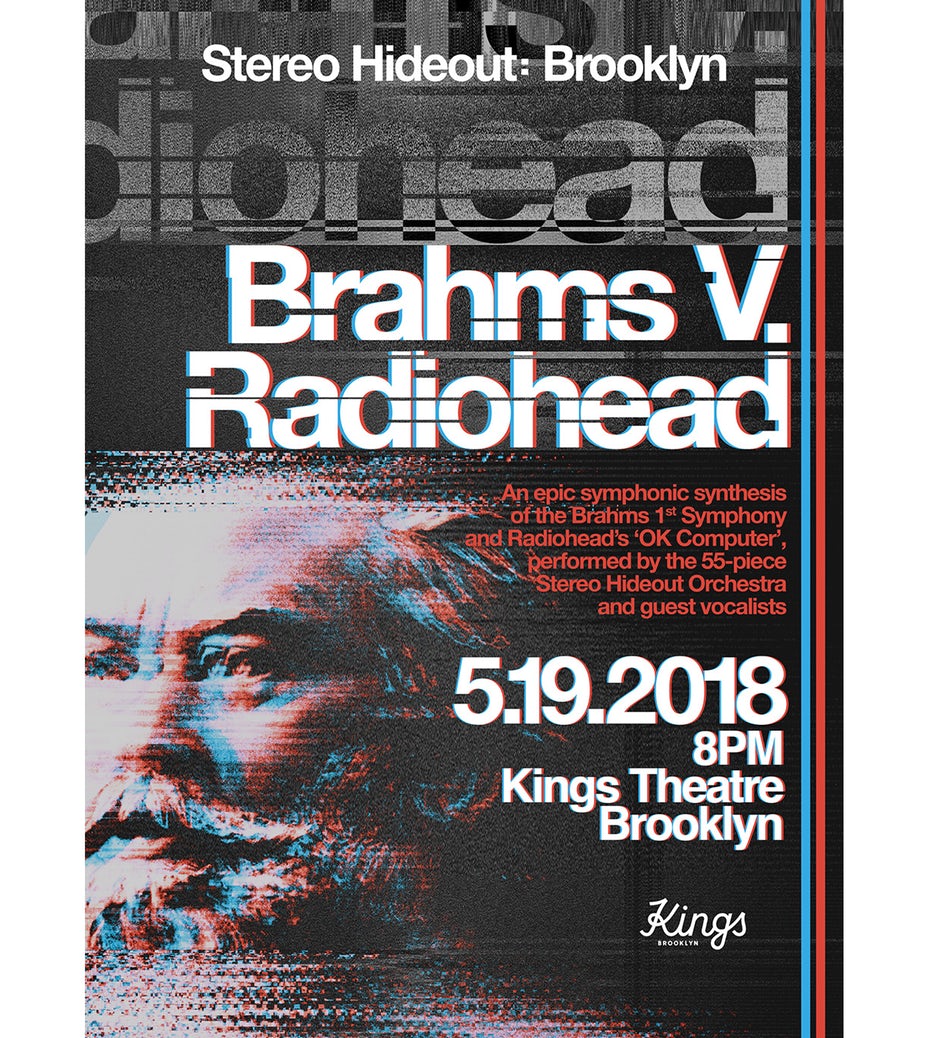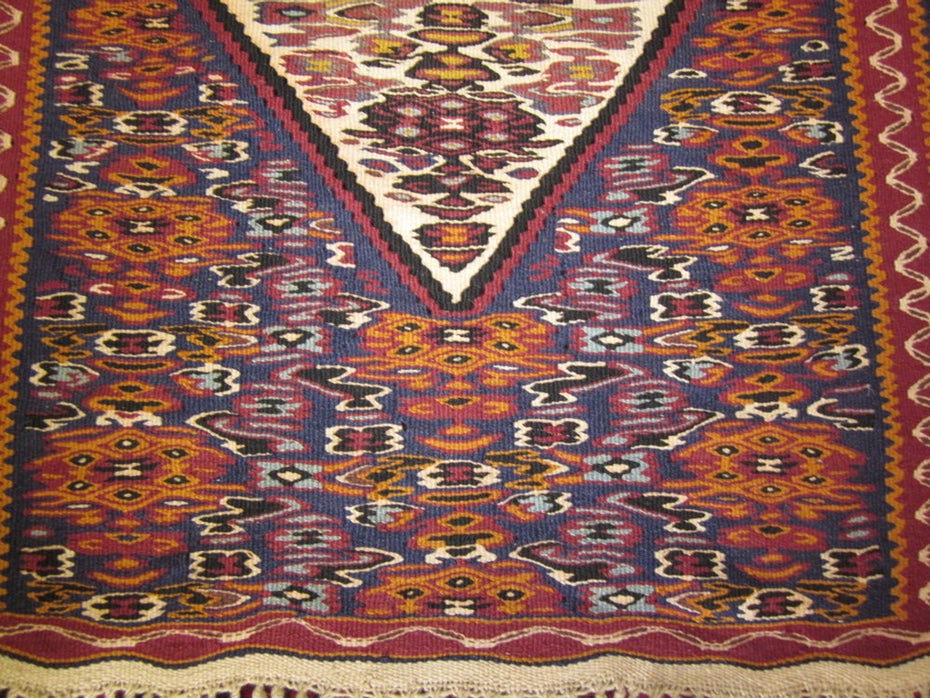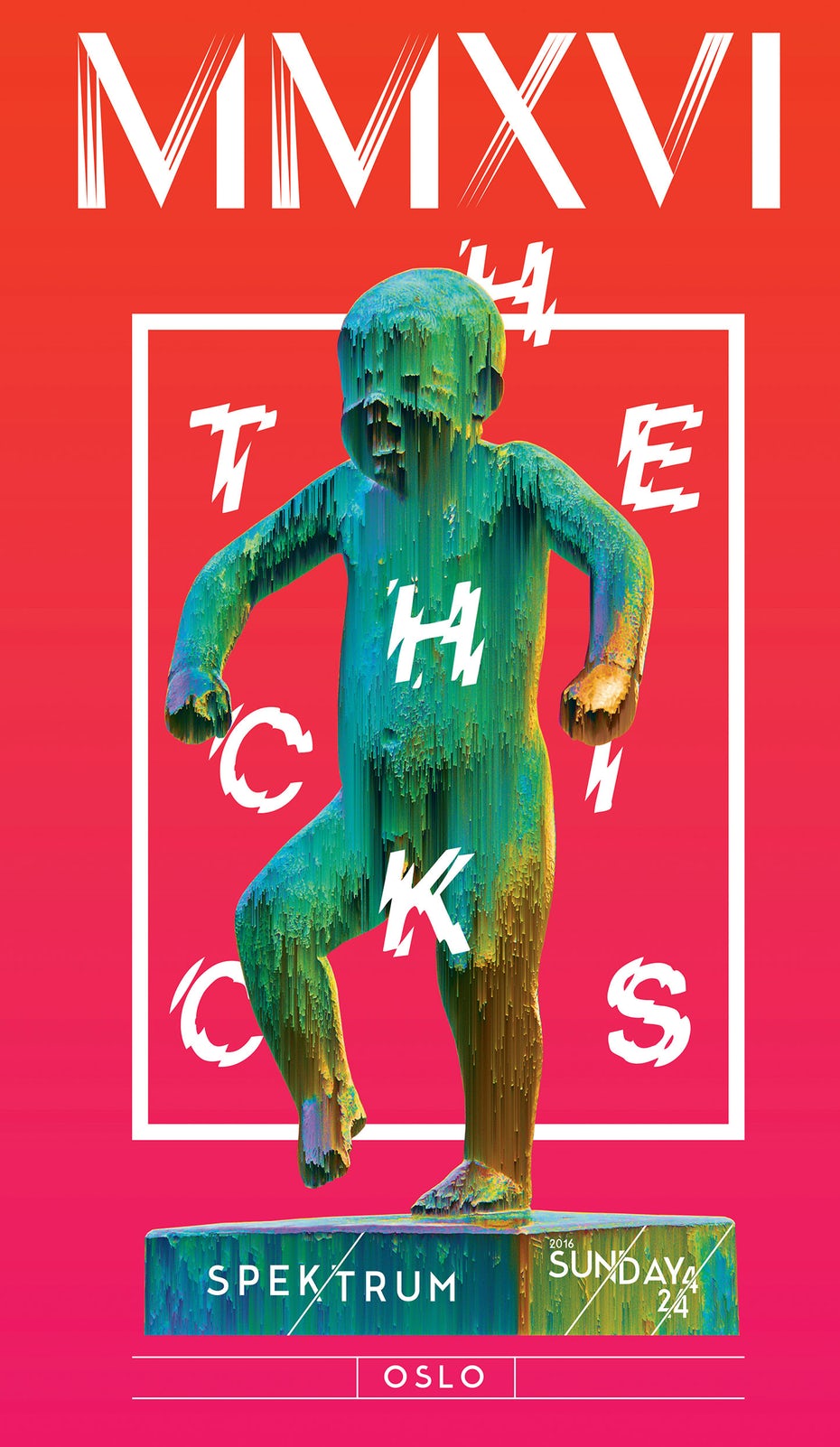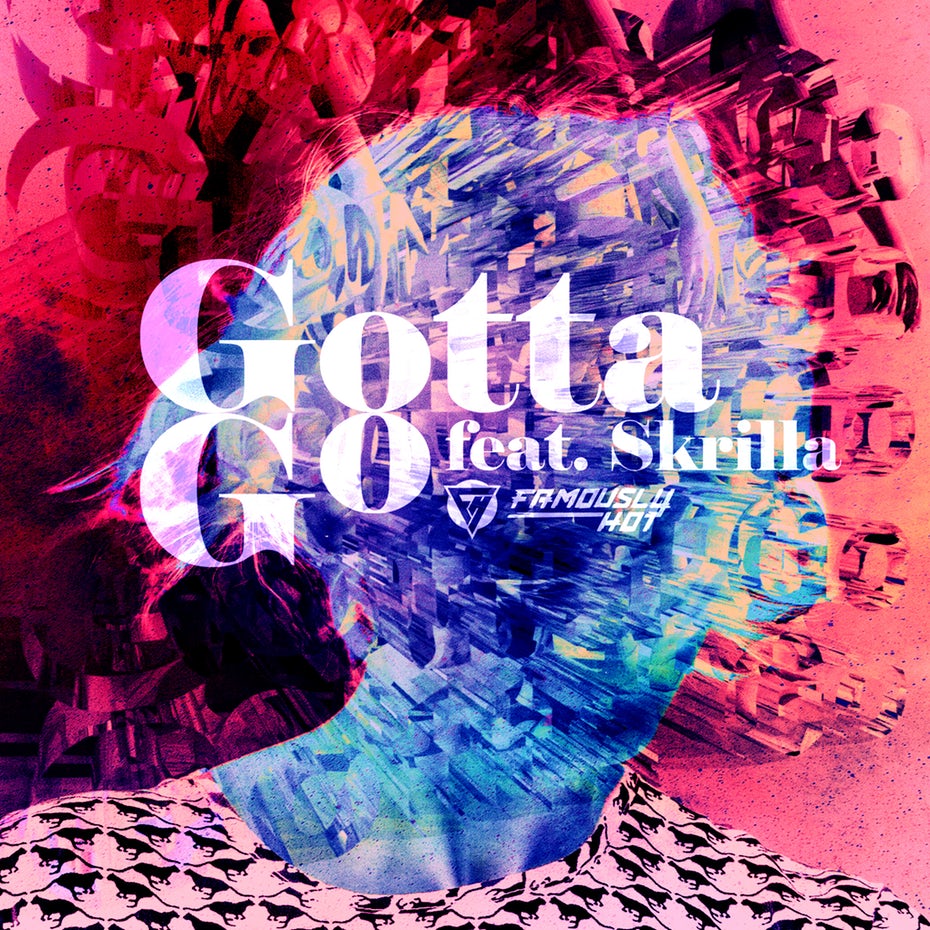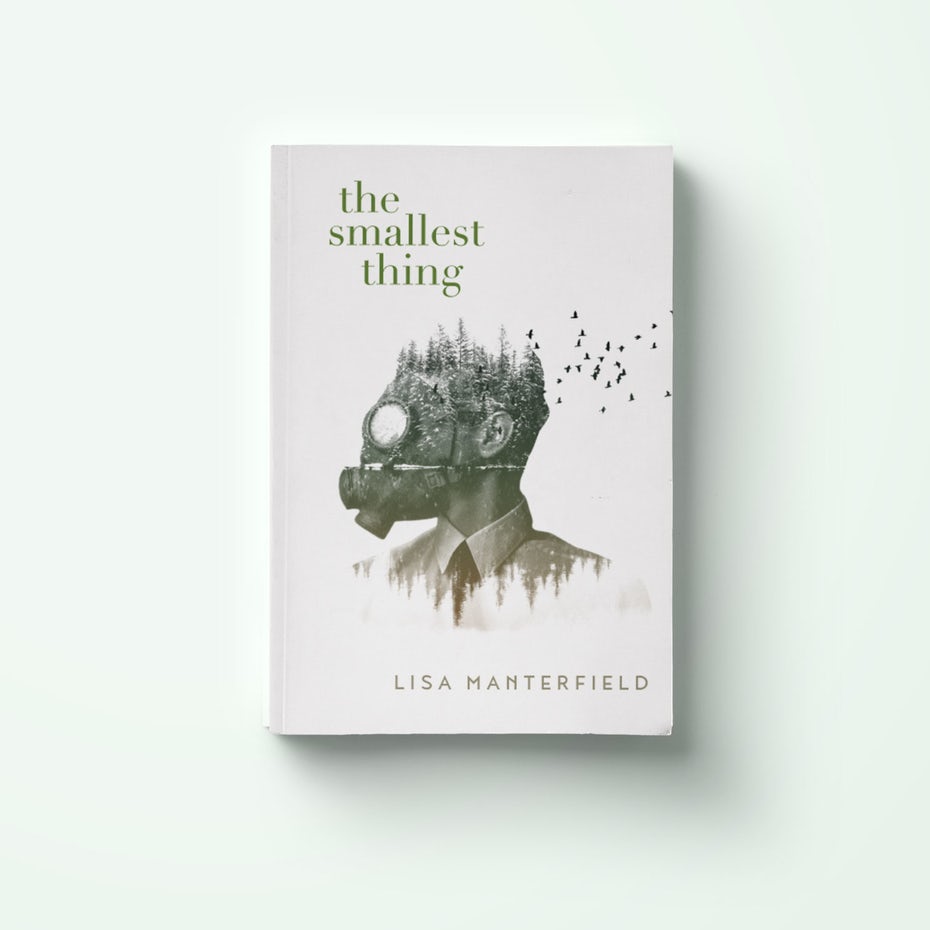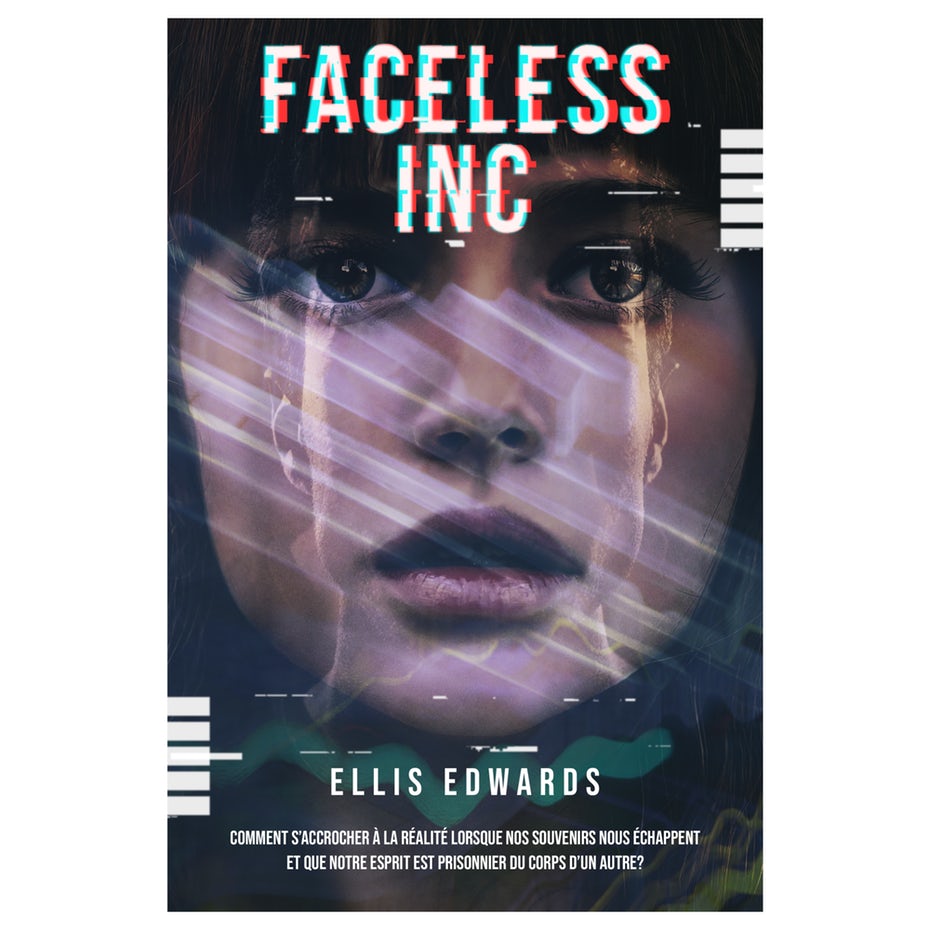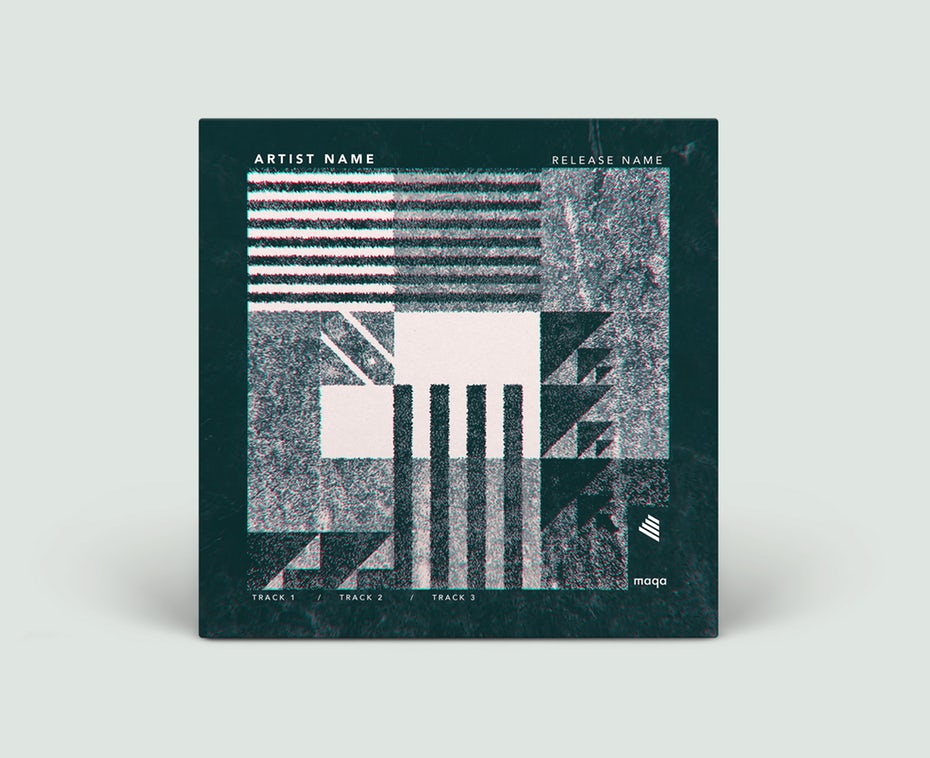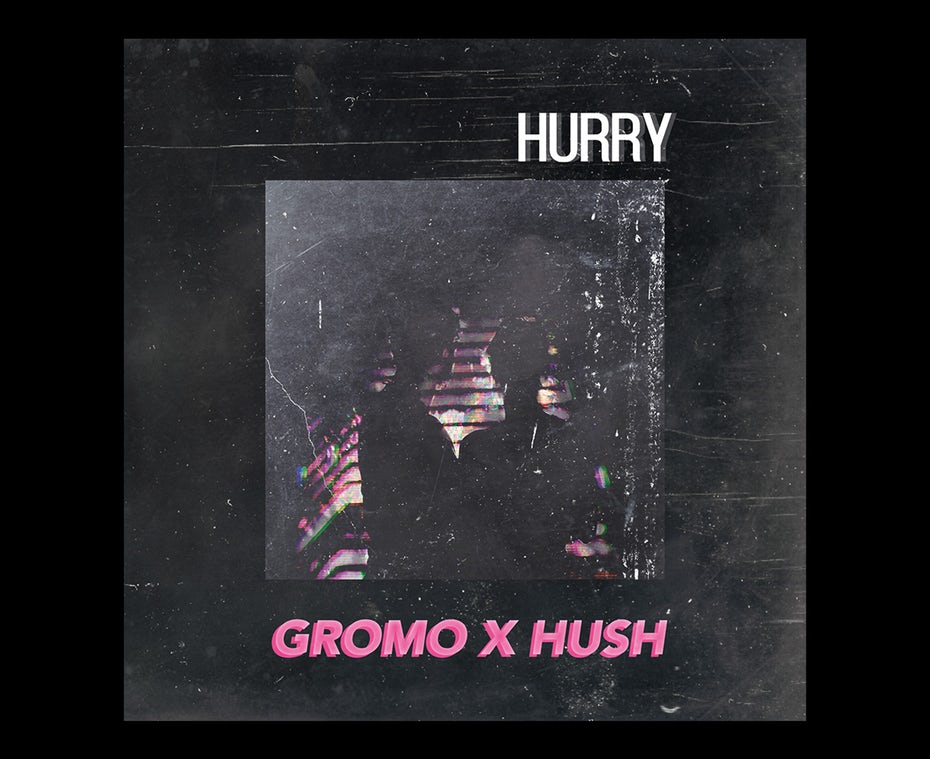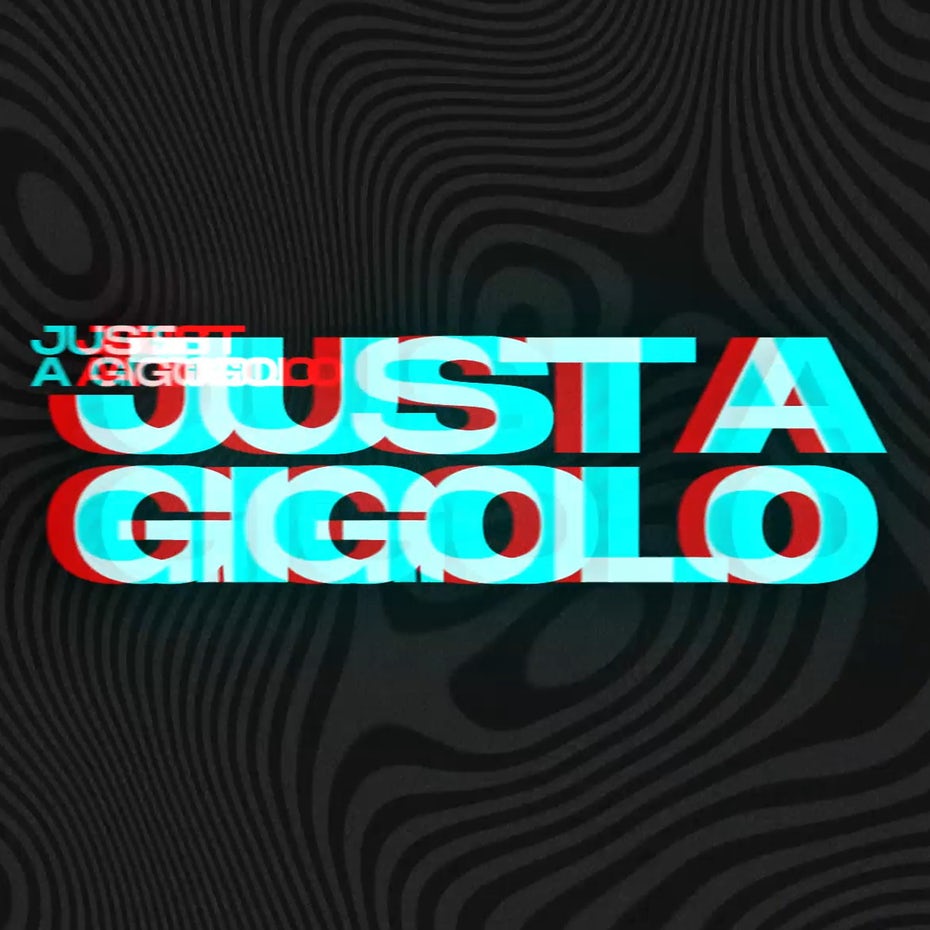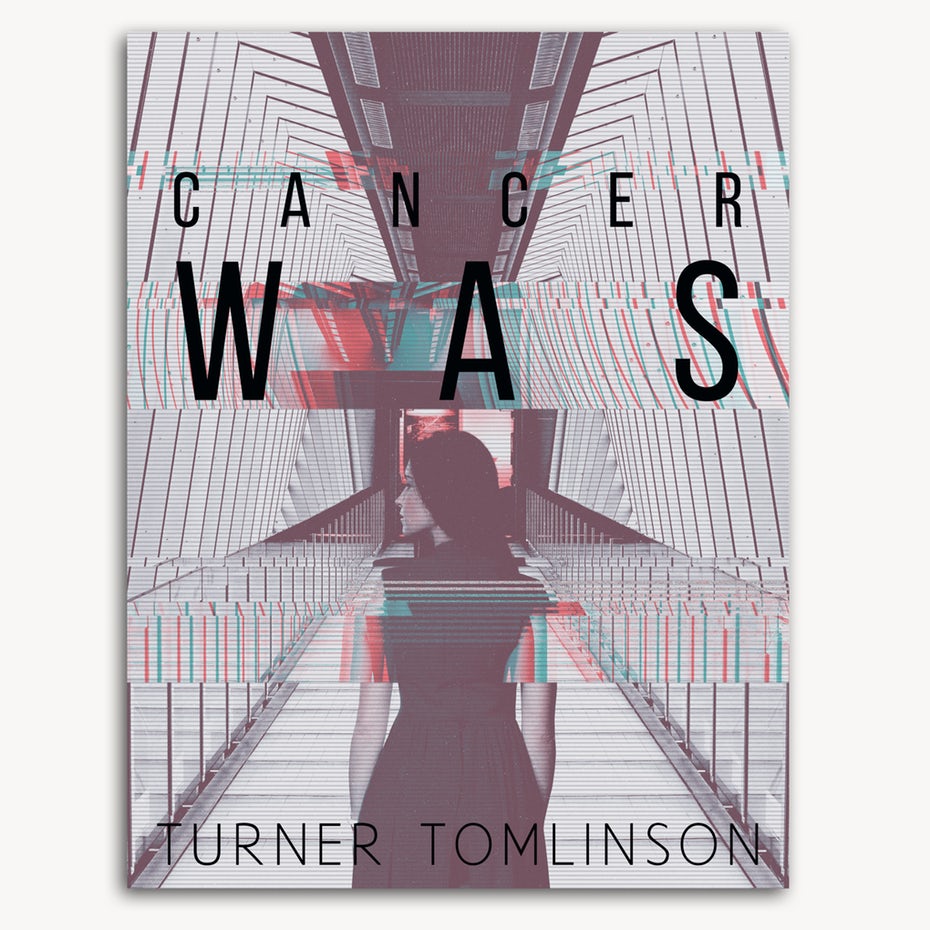
故障艺术设计教程:历史的内观与现代潮流的最佳运用
魔术贴,冰棒和发酵都有一些共同之处:它们是快乐事故的产物。故障艺术也是如此:由数字碰撞造成的无意的扭曲导致了图形设计的一个完整的、令人费解的子类型
故障艺术是品牌的绝佳机会。不仅形式视觉上令人惊叹,故障艺术的固有挑衅性质在产品背后创造了令人难忘的形象。虽然这种以DIY为重点,看起来很随意的艺术形式似乎没有指导原则,但重要的是要了解它的来源和开始的方式,如果你刚接触到小故障。
什么是故障艺术?
故障艺术是一种视觉风格,其特点是将数字或模拟误差用于审美目的,无论是故意的(即“伪造故障”和通过设计获得类似的美学)还是偶然的(在没有人的情况下系统内部的真实表现)介入)。
这些美妙的快乐事故证明,电子技术仍然是表达和创造的开放媒介,因此为设计师重新构想产品,标识,排版等创造了另一条途径。
Shutterstock的创意总监Terrence Morash解释说:“[故障艺术]存在一种受控制的缺陷,它提醒人们设计的技术要素。它将技术可视化为具有纹理和图案的组合,但并不完美。“
故障艺术的历史
术语“故障”本身源于工程师和宇航员,用来解释他们所使用的技术中的故障:宇宙飞船和火箭硬件。但是视觉美学可以追溯到20世纪初,通过立体主义绘画,抽象短片和类似像素的地毯设计中的扭曲形式,类似于8位视频游戏景观。
快进到现代,我们经常在流行文化中看到这种扭曲的图像,作为一种集体的承认,科技是如何参与到我们的日常生活中的,是多么容易被破坏。
The Glitch Moment(um)的作者Rosa Menkmen 解释了流行文化中的故障艺术的二重性:“一方面,有战术和批评艺术家使用这种技术来批评流行文化,另一方面技术现在非常活跃,也是同一种文化的一部分。“
故障艺术卷土重来
作为一种运动的小故障艺术可以与朋克音乐相提并论。它的复兴也对以前似乎无法触及的媒体提出了挑战:光滑,完美,不切实际。
但是,故障艺术不仅仅是一种庆祝不完美和批判的当代文化运动。
它甚至通过主流媒体渗透 - 这是一个有趣的进展,因为它经常出现在与流行文化和趋势的对立中。
但是,故障艺术的普及确实传达了对系统故障以及我们自身脆弱,且通常与技术的脆弱关系的广泛认可。
设计界现在已经完全接受了这种以技术为中心的美学,许多出版物都预测,未来几年将会以越来越多的非传统方式继续出现故障艺术。
品牌如何使用故障艺术
由于它的扭曲,故障艺术本质上是神秘的,品牌可以利用这一点在他们的外观中创造出一种魅力。还有一种永恒性,伴随着未来主义和复古的矛盾平衡。但更重要的是,故障艺术比美感更能吸引人,品牌将不得不考虑与故障艺术相关的反叛,挑衅的价值观是否适合他们的观众。
这种技术驱动,反叛和政治上很有艺术性的艺术,有能力吸引那些与抵抗和运动对抗谷物的观众。例子可以从用扭曲的镜头来表达怀旧之情的口袋妖怪来看,是专注于创新和透明度的科技公司创造的,这些公司的产品承诺要彻底改变我们的做事方式。
小故障艺术并不总是充满了大胆的扭曲,当你想要捕捉故障运动的氛围而不致力于一种可能对实用品牌来说过于前卫的视觉风格时,它更微妙的化身可能是有用的。
故障艺术设计技巧
我们经常会看到毛刺带来的具体艺术效果,你将希望复制这些技术以创建令人信服的故障艺术设计。
在一天结束时,无论是故意还是故意,“破碎”的图像都来自破碎的数据,而这个错误就是你试图通过人工方式进行通信的原因。
话虽如此,让我们来看看最常见的故障艺术设计风格。
像素化
计算机图像是由像素组成的,当这些像素中的几个不亮时,最终会出现故障。像素化的效果是最有效的,离开外部和抽象的意见空间内。
光泄漏
通过模拟胶片相机体内的间隙,允许光线泄漏到通常的防光胶片室中(从而使胶片暴露在额外的光线下)的现象,设计师可以在其设计中产生烧尽效果。如果你通过阴影或反射创建感兴趣的点,则会为设计带来动态特征。
双曝光
通过将多个图像叠加在一起,设计师可以执行一种空灵的,机器内的鬼影效果。相应地选择组合和位置,重要的是要注意在此应用程序中使用的颜色,以免压倒图像的主体。
噪音与颗粒
设计师可以增加颗粒状的伪像或噪音,以重现旧电影或模拟广播的外观。这个小故障中最常见的例子之一就是旧VHS视频中出现的颗粒状条带。
颜色退化
彩色的液化和模糊使用传达了系统故障。因为颜色本身在视觉上要求很高,所以要注意设计的其他元素,以确保最终结果不会太大,无法传达你想要达到的效果。
纹理
与颜色使用一样,模糊和不可预测的纹理以及不对称的几何形状也让人感觉到一种艺术感,这是一种审美缺陷。这些可以作为背景图像或在设计的前景中引人注目的抽象作品。
故障字母
选择通信故障的字体,认为VHS已损坏。字母周围有锯齿状或波浪状线条和模糊效果的大写字母也可以象征运动。
或者,你可以通过拼接、复制字母以创建双曝光结果、添加柔和的霓虹阴影、拉长或合并字母形式来扭曲自己的字母。
用正确的方式使用故障艺术
虽然故障艺术可能看起来像一些华丽的现代潮流,但它不会很快消失。因为技术的进步越多,该技术的分解机会就越多,设计师就会在视觉上重新解释这些缺陷。
也许这种艺术形式最吸引人的方面之一是其高度实验性,即使它为制造者创造了一项具有挑战性的任务。制造巨大故障的过程可能看起来令人生畏,但审美创新的回报值得付出努力。随着故障艺术和技术的进步,未知的新领域将永远呈现在这个不断扩大的设计领域。